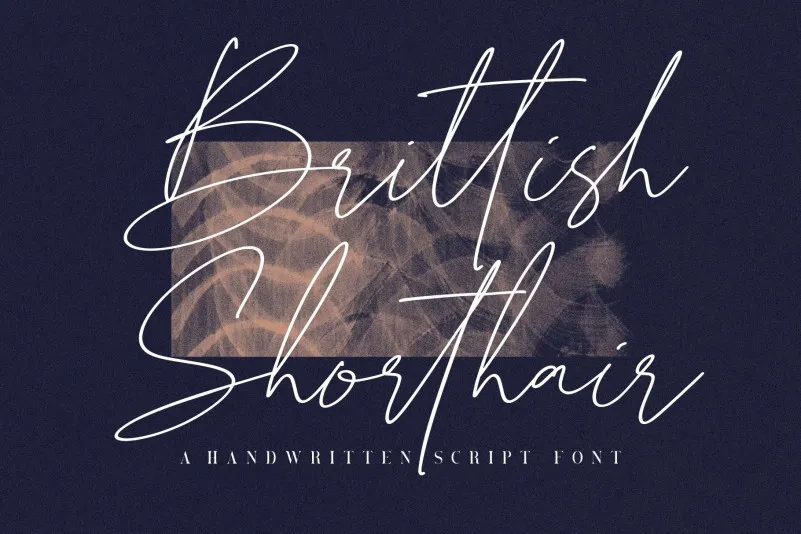
British Shorthair Script Font – Download Grátis
A British Shorthair Script Font é uma elegante tipografia à mão escrita criada pela Hanzel Space. Com suas curvas únicas e fluxo inebriante, essa fonte traz um toque delicado e elegante perfeito para projetos de branding, logomarcas, designs de casamentos, postagens no redes sociais, anúncios, embalagens de produtos, design de produtos, etiquetas, websites, fotografia, marca d’água, convites e material de estaçãoaria. Além disso, é perfeita para qualquer projeto que precise do charme da escrita à mão.